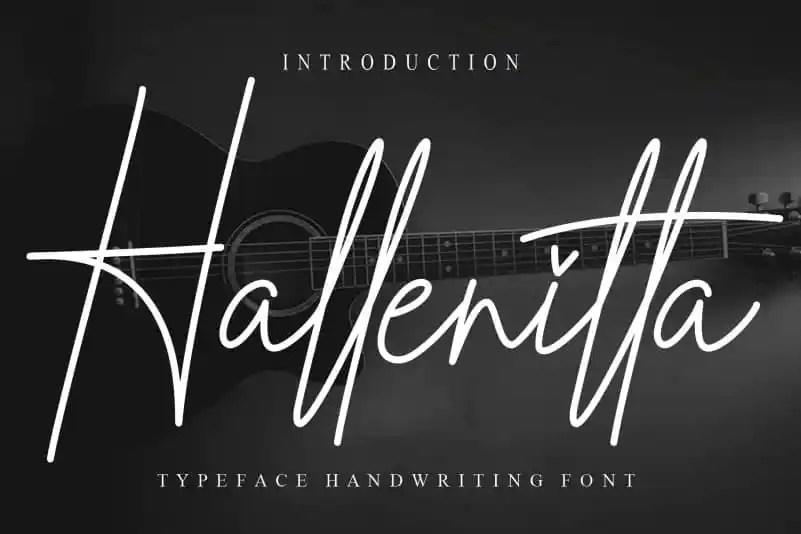
Hallenitta Handwritten Font – Fonte Grátis
Hallenitta Handwritten Font
Esta página apresenta a Hallenitta Handwritten Font, uma elegante escolha para designers que buscam transparência e autenticidade em seus trabalhos digitais. Com traços suaves e uma rica escrita manuscrita, esta font oferece um toque único que se destaca nas páginas onde é utilizada. Suavemente fluida e com um ar de intimidade natural, Hallenitta é perfeita para aplicações em conteúdo pessoal ou gráficos semelhantes. Os designers que valorizam a mão do autor e uma experiência visual confortável podem adquirir esta fonte, que traz consigo o toque único dos artistas que criaram cada caractere. Esta font é ideal para sites de blog, designs de carrosel ou qualquer formato em que deseja inserir um tom autêntico. Sua escrita delicada e detalhada oferece uma experiência visual agradável para seus usuários, tornando Hallenitta uma escolha inteligente para os designers que querem transmitir uma mensagem semelhante à do próprio autor por trás da letra. Com uma paleta de características únicas, cada caractere é um pouco mais profundo e rico em detalhes. Esta fonte oferece tanto a quem valoriza a simplicidade quanto a quem aprecia a profundidade e riqueza que só o traço de mão pode fornecer. E aqui está Hallenitta Handwritten Font para você, para fazer do seu design algo ainda mais especial.